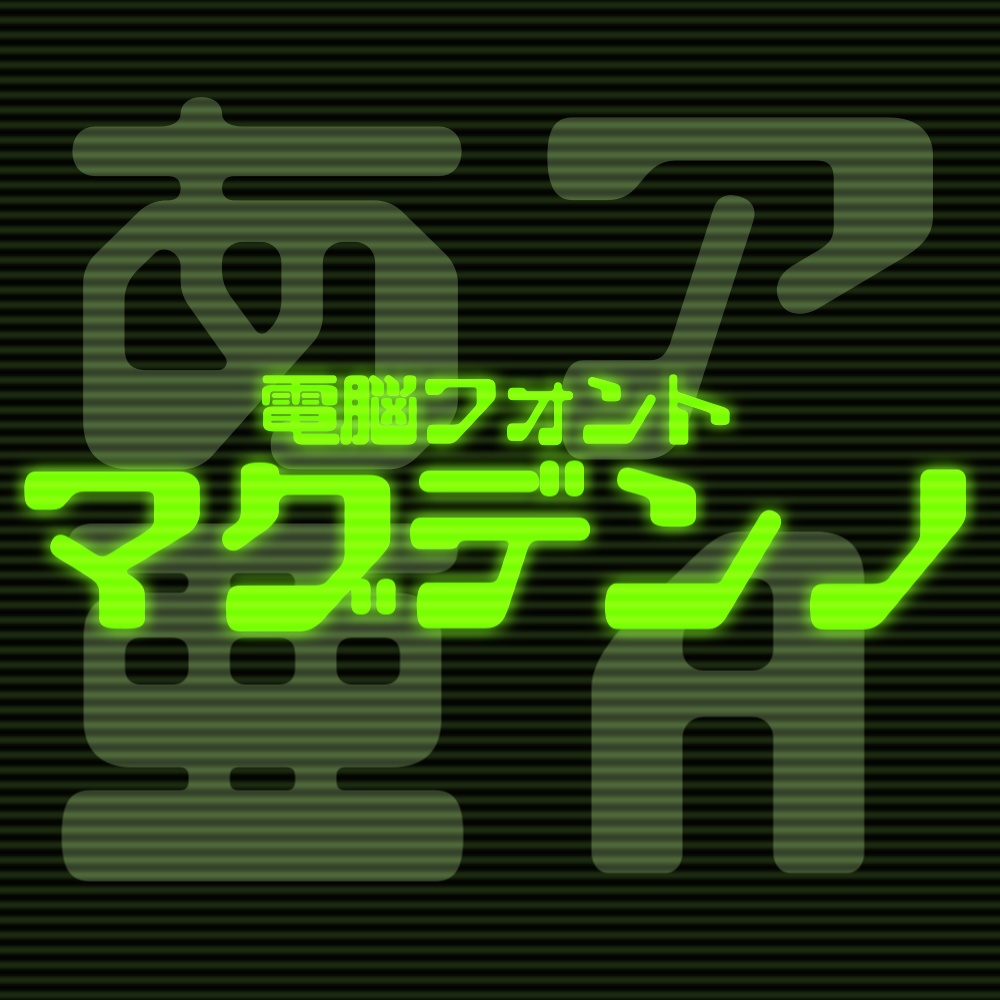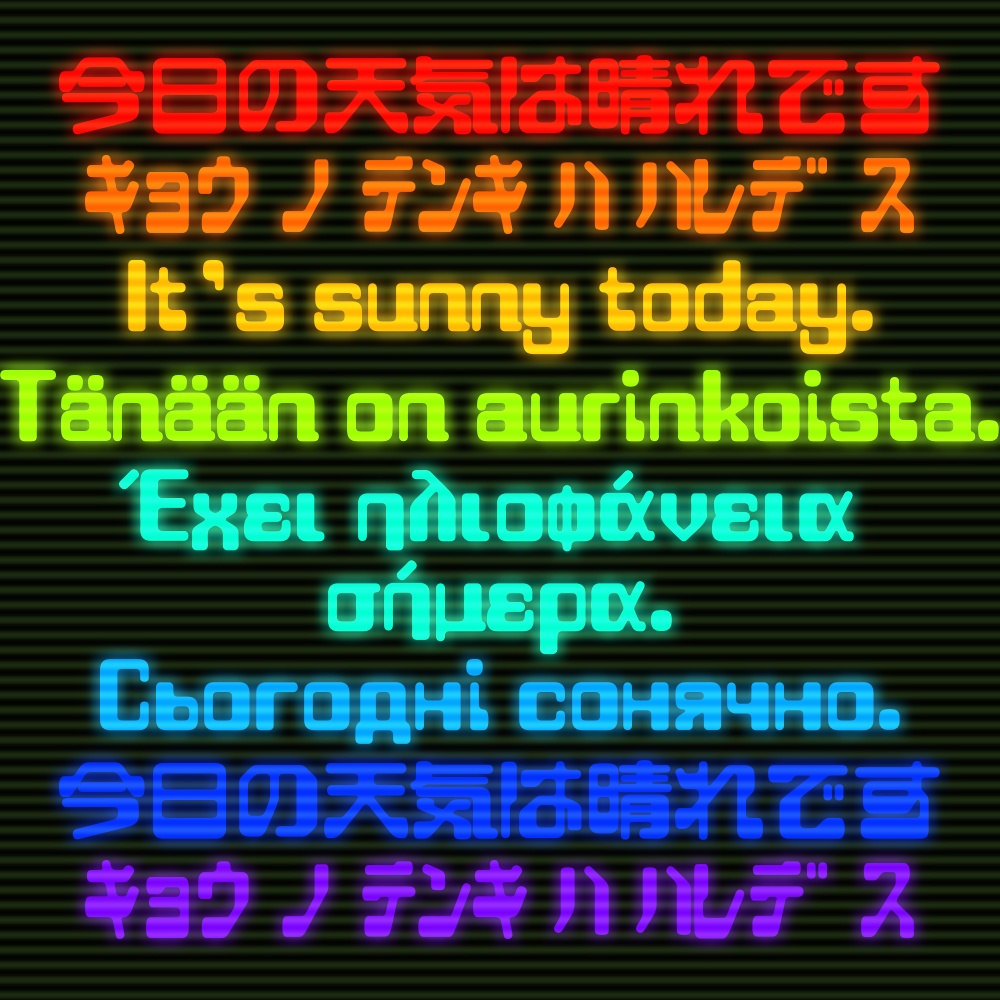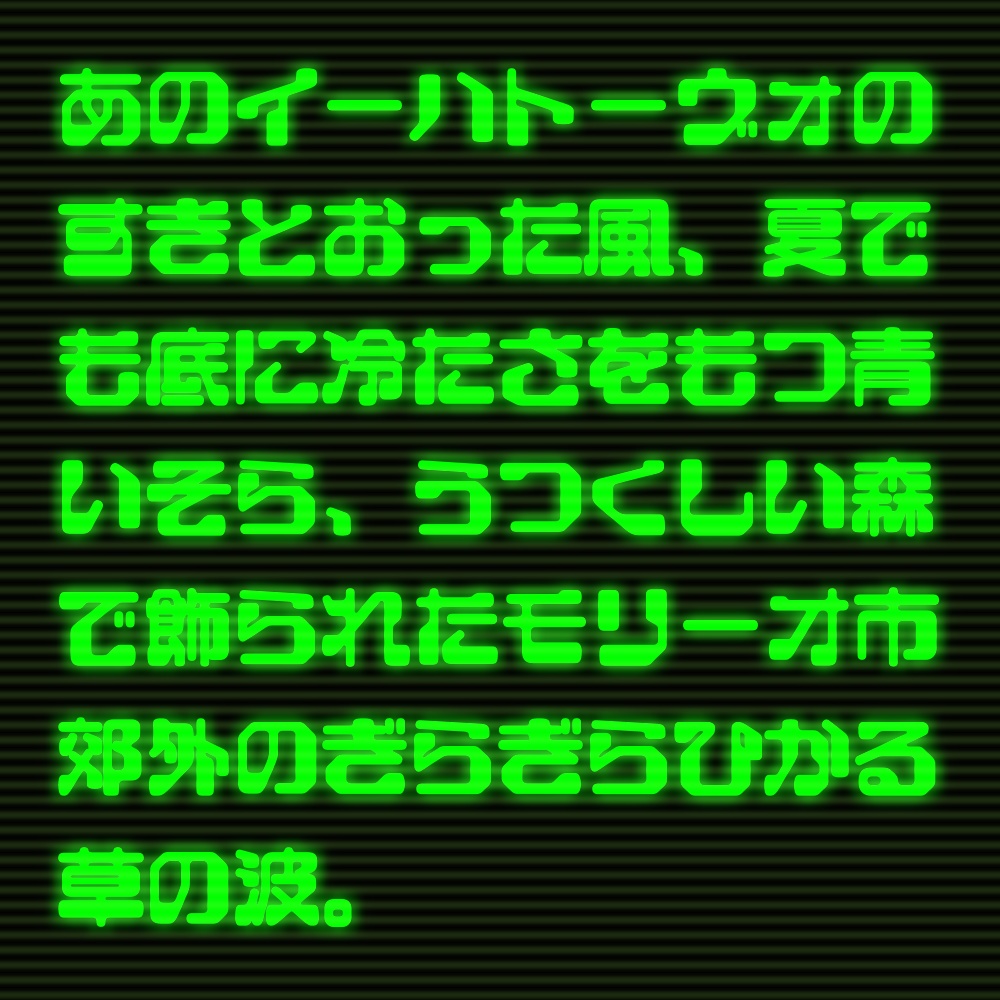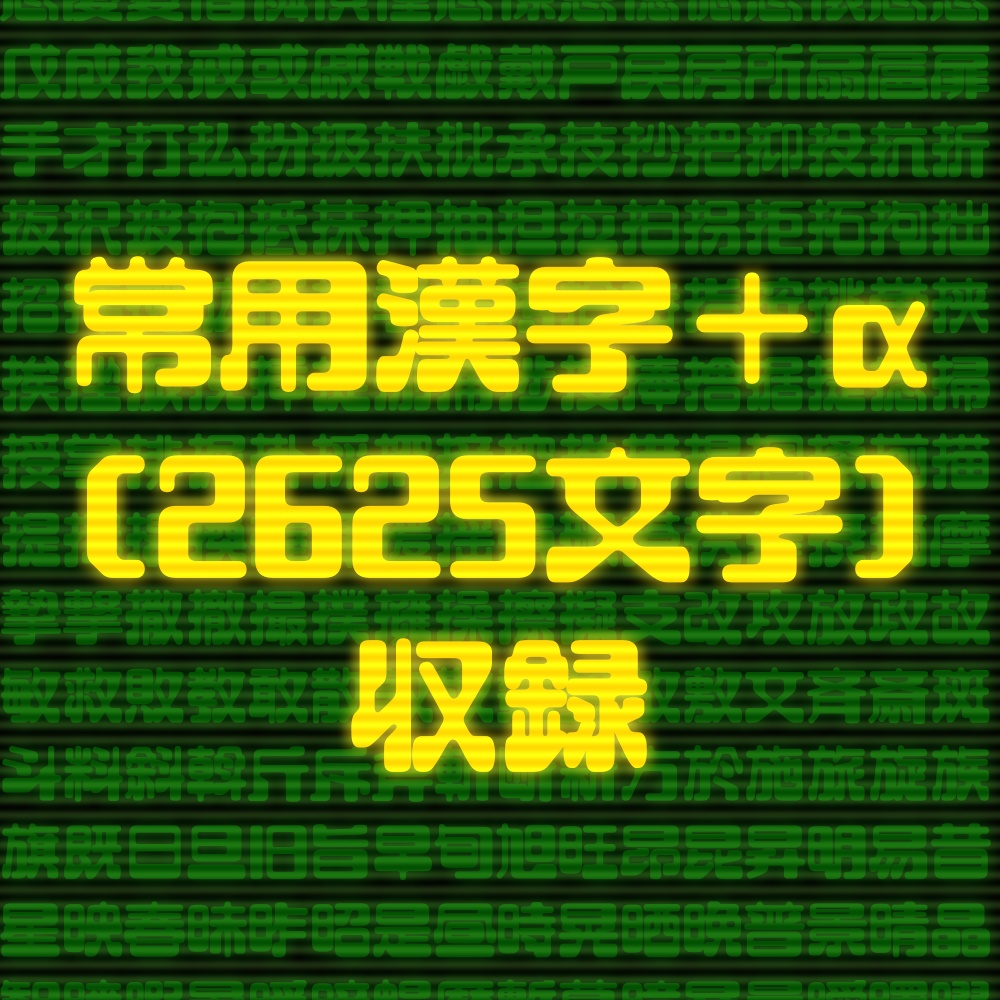
【日本語フォント】マグデンノ
電脳世界をイメージしたフォントです。 アクセント付き欧文文字が豊富なので、作品のローカライズなどにもご活用頂けます。
対応字種について
◆主要な記号とアクセント付きアルファベット・一部のギリシャ文字・一部のキリル文字・以下の漢字(常用漢字+αの2625文字)に対応しています。 ◆詳しい対応字種は<http://pg-types.com/対応字種.pdf>をご参照ください。 一丁七万丈三上下不与丑且世丘丙両並中串丸丹主丼乃久之乏乖乗乙九乞乱乳乾亀了予争事二云互五井些亜亡交亥享京亭亮人仁今介仏仔仕他付仙仝代令以仮仰仲件任企伊伎伏伐休会伝伯伴伸伺似佃但位低住佐佑体何余作佳併使例侍供依価侮侯侵侶便係促俊俗保信俣修俳俵俸俺倉個倍倒候借倣値倫倶倹偉偏停健偲側偵偶偽傍傑傘備催傭傲債傷傾僅働像僕僚僧僻儀億儒償優元兄充兆先光克免児党入全八公六共兵其具典兼内円冊再冒冗写冠冥冨冬冴冶冷凄准凌凍凜凝凡処凪凶凸凹出函刀刃分切刈刊刑列初判別利到制刷券刹刺刻剃則削前剖剛剣剤剥副剰割創劇力功加劣助努劫励労効劾勃勅勇勉動勘務勝募勢勤勧勲勾勿匂包化北匠匹区医匿十千升午半卑卒卓協南単博占卯印危即却卵卸卿厄厘厚原厭厳去参又及友双反収叔取受叙叡口古句叩只叫召可台史右叶号司各合吉同名后吏吐向君吟吠否含吸吹呂呆呈呉告呑周呪味呼命和咲咽哀品哉員哭哲哺唄唆唇唐唖唯唱唾啄商問啓善喉喋喚喜喝喩喪喫喰営嗅嗣嘆嘗嘘嘩嘱嘲噂噌噛器噴嚇囚四回因団困囲図固国圏園土圧在圭地坂均坊坐坑坙坪垂型垢垣埃埋城埜域埠執培基埼堀堂堅堆堕堤堪堰報場堵堺塀塁塊塑塔塗塙塚塞塩塾境墓増墜墨墳墾壁壇壊壌壕士壮声壱売変夏夕外多夜夢大天太夫央失夷奄奇奈奉奏契奔奥奨奪奮女奴好如妃妄妊妖妙妥妨妬妹妻姉始姐姓委姪姫姻姿威娘娠娯婆婚婦婿媒媛嫁嫉嫌嫡嬉嬢嬰子孔字存孝季孤学孫宅宇守安完宍宏宕宗官宙定宛宜宝実客宣室宥宮宰害宴宵家容宿寂寄寅密富寒寛寝察寡寧審寮寸寺対寿封専射将尉尊尋導小少尚尤就尺尻尼尽尾尿局居屈届屋屍展属屠層履屯山岐岡岩岬岳岸峠峡峨峰島峻崇崎崖崩嵐嶺川州巡巣工左巧巨差己巳巴巷巻巾市布帆希帖帝帥師席帯帰帳常帽幅幌幕幡幣干平年幸幹幻幼幽幾庁広庄床序底店府度座庫庭庵庶康庸廃廉廊廣延廷建弁弄弊式弐弓弔引弘弟弥弦弧弱張強弾彅当彗彙形彦彩彫彰影彷役彼彿往征径待律後徐徒従得御復循微徳徴德徹心必忌忍志忘忙応忠快念怒怖怜思怠急性怨怪怯恋恐恒恣恥恨恩恭息恵悉悔悟悠患悦悩悪悲悴悶悼情惑惚惜惧惨惰想惹愁愉意愚愛感慄慈態慌慎慕慟慢慣慧慨慮慰慶憂憎憐憤憧憩憬憲憶憾懇懐懲懸戊成我戒或戚戦戯戴戸戻房所扇扈扉手才打払扮扱扶批承技抄把抑投抗折抜択披抱抵抹押抽担拉拍拐拒拓拘拙招拝拠拡括拭拳拶拷拾持指按挑挙挟挨挫振挽挿捉捌捕捗捜捧捨据捷捻掃授掌排掘掛採探接控推措掲掴掻揃描提揖揚換握揮援揺損搬搭携搾摂摘摩摯撃撒撤撮撲擁操擦擬支改攻放政故敏救敗教敢散敦敬数整敵敷文斉斎斑斗料斜斡斤斥斧斬断新方於施旅旋族旗既日旦旧旨早旬旭旺昂昆昇明易昔星映春昧昨昭是昼時晃晒晩普景晴晶智暁暇暑暖暗暢暦暫暮暲暴曇曖曙曜曲曳更書曹曽替最月有朋服朕朗望朝期木未末本札朱朴机朽杉李杏材村杓杖束条来杯東松板析枕林枚果枝枠枢枯架柄柊柏某染柔柚柱柳柴柵査柿栃栄栓栖栗校株核根格栽桁桂桃案桐桑桜桝桟桶梅梓梗梨械梱梶棄棉棋棒棚棟森棲棺椀椅植椎椛検楊楓業楳極楷楼楽概榊榎榛構槌様槙槻槽標樟模権横樫樹樽橋橘機橿檎檬檸櫓櫻欄欠次欣欧欲欺欽款歌歓止正此武歩歪歯歳歴死殆殉殊残殖殲殴段殺殻殿毀毅母毎毒比毛毬氏民気水氷永氾汁求汎汐汗汚汝江池汰決汽沃沈沌沓沖沙没沢沫河沸油治沼沿況泉泊泌法泡波泣泥注泰泳洋洗洛洞津洩洪洲活派流浄浅浜浦浩浪浮浴海浸消涌涙涯液涼淀淑淘淡淫深淳淵混添清渇済渉渋渓渚減渡渥渦温測港湊湖湘湜湧湯湾湿満源準溜溝溢溶溺滅滋滑滝滞滴漁漂漆漉漏演漕漠漢漫漬漸潔潜潟潤潮潰澄澱激濁濃濠濫濯濵瀕瀞瀧瀬灘火灯灰灼災炉炊炎炭炸点為烈烏焔焙焚無焦然焼煉煎煙煤照煩煮煽熊熟熱熾燃燈燐燕燥燦燭爆爪爵父爺爽片版牌牙牛牡牢牧物牲特犠犬犯状狂狐狗狙狛狩独狭狼狽猛猟猪猫献猶猿獄獅獣獲玄率玉王玩玲珂珊珍珠珪班現球理琉琥琦琴琵琶瑙瑚瑛瑞瑠瑳璃璟璧環璽瓜瓦瓶甘甚甜生産用田由甲申男町画界畏畑畔留畜畝略番異畳畷畿疎疑疫疲疼疾病症痕痘痛痢痩痴瘍瘤療癌癒癖癪発登白百的皆皇皐皮皿盆益盗盛盟監盤目盲直相盾省眉看県真眠眩眺眼着睡督睦瞥瞬瞭瞳矛矢知矩短矯石砂研砕砲破砺硝硫硬碁碑碧確磁磐磨磯礁礎礫示礼社祀祇祈祉祐祖祝神祠祥票祭禁禄禅禍福秀私秋科秒秘租秦秩称移稀程税稚稜種稲稼稽稿穀穂積穏穢穣穫穴究空穿突窃窒窓窟窪窮窯窺立竜章竣童端競竹笑笛笠符第笹筆等筋筐筑筒答策箇箋箕算管箱箸節範篇築篠篤篭簡簿籍籠米籾粉粋粒粗粘粛粟粧精糖糟糧糸系糾紀約紅紋納紐純紗紙級紛素紡索紫累細紳紹紺終組経結絞絡絢給統絵絶絹継続綬維綱網綴綻綾綿緊総緑緒線締編緩緯練緻縁縄縛縞縦縫縮績繁繊繋織繕繭繰纂缶罠罪罫置罰署罵罷羅羊美羞群羨義羽翁翌習翠翻翼老考者耐耕耗耳耶耽聖聞聡聯聲聴職肇肉肋肌肖肘肝股肢肥肩肪肯育肺胃胆背胎胞胡胴胸能脂脅脆脇脈脊脚脱脳腎腐腔腕腫腰腸腹腺膏膚膜膝膠膨膳臆臓臣臥臨自臭至致臼興舌舎舗舘舞舟航舵舶舷船艇艦良色艶芋芝芥芦芭芯花芳芸芹芽苑苔苗苛若苦苫英苺茂茄茅茎茜茨茶草荏荒荘荷荻莫菅菊菌菓菜華菱萌萎萩落葉著葛董葦葬葵蒜蒸蒼蓄蓋蓑蓬蓮蔑蔓蔦蔵蔽蕉蕎蕨蕩薄薦薪薫薬藍藤藩藻蘭虎虐虚虜虞虫虹虻蚊蚕蛇蛍蛭蛮蜂蜜蝋蝕融螺蠍蠢血衆行衒術街衛衝衡衣表衰衷袋袖被裁裂装裏裔裕補裟裸製裾複褐褒襟襲西要覆覇見規視覗覚覧親観角解触言訂訃計討訓託記訝訟訣訪許訳訴診註証詐詔評詞詠詣試詩詫詮詰話該詳誇誉誌認誓誕誘語誠誤説読誰課誹誼調談請諏諒論諜諦諧諭諮諸諾謀謁謂謄謎謙講謝謡謬謳謹識譚譜警議譲護讃讐谷豆豊豚象豪豹貌貝貞負財貢貧貨販貪貫責貯貰貴貶買貸費貼貿賀賂賃賄資賊賎賑賓賛賜賞賠賢賤賦質賭購贈赤赦走赴起超越趣足跋距跡路跳践踊踏踪蹄蹴躍躓身躯車軌軍軒軟転軸軽較載輌輔輝輩輪輸輿轄轍轟轢辛辞辣辱農辺辻込辿迂迄迅迎近返迫迭述迷追退送逃逅逆透逐逓途逗這通逝速造逢連逮週進逸逼遁遂遅遇遊運遍過道達違遜遠遡遣遥適遭遮遵遷選遺遼避邂還邑那邦邪邸郁郊郎郡部郭郵郷都鄙酉酌配酎酒酔酢酪酬酵酷酸醍醐醒醜醤醸采釈里重野量金釘釜針釣鈍鈴鉄鉛鉢鉱銀銃銅銘銭鋭鋳鋼錆錠錦錨錬錮錯録鍋鍛鍵鍾鎌鎖鎚鎧鎮鏑鏡鐘鑑長門閃閉開閑閒間関閣閤閥閲閾闇闊闘阜阪防阻阿附降限陛院陣除陥陪陰陳陵陶陸険陽隅隆隈隊階随隔隙際障隠隣隷隻隼雀雄雅集雇雌雑離難雨雪雰雲零雷電需震霊霜霞霧露靏青静非面革靴鞄鞍鞘鞠鞭韓韮音韻響頁頂頃項順須預頑頒頓領頬頭頰頷頸頻頼題額顎顔顕願顚顛類顧顰風飛食飢飯飲飴飼飽飾餃餅養餌餓館首香馬駄駅駆駐駒駿騎騒験騙騨騰驚骨骸髄髏髑高髙髪鬱鬼魁魂魅魍魎魑魔魚魬鮎鮪鮫鮮鯉鯖鯨鯵鰐鰯鰻鱒鱗鳥鳩鳳鳴鴎鴛鴨鴫鴬鴻鵜鵠鶏鶴鷗鷲鷹鹵鹿麓麗麦麴麺麻黄黎黒黙鼓鼠鼻齟齢齧齬龍塚﨑